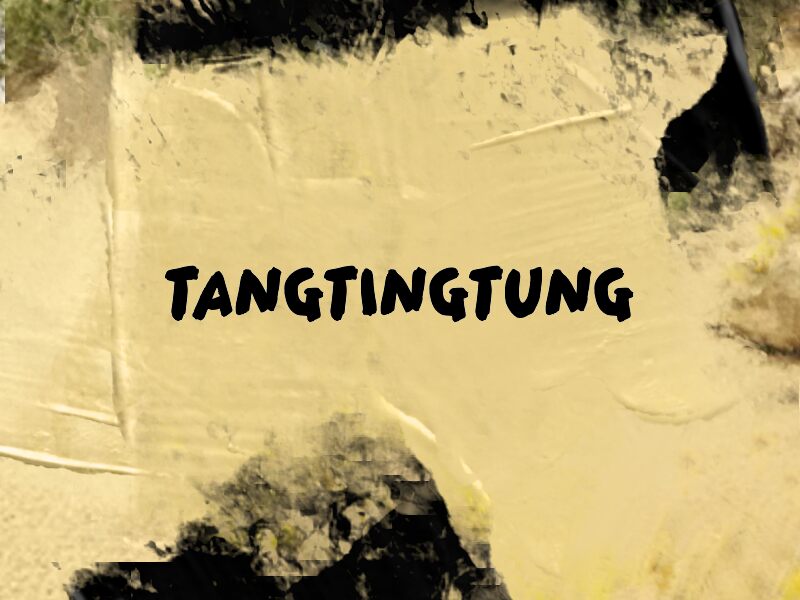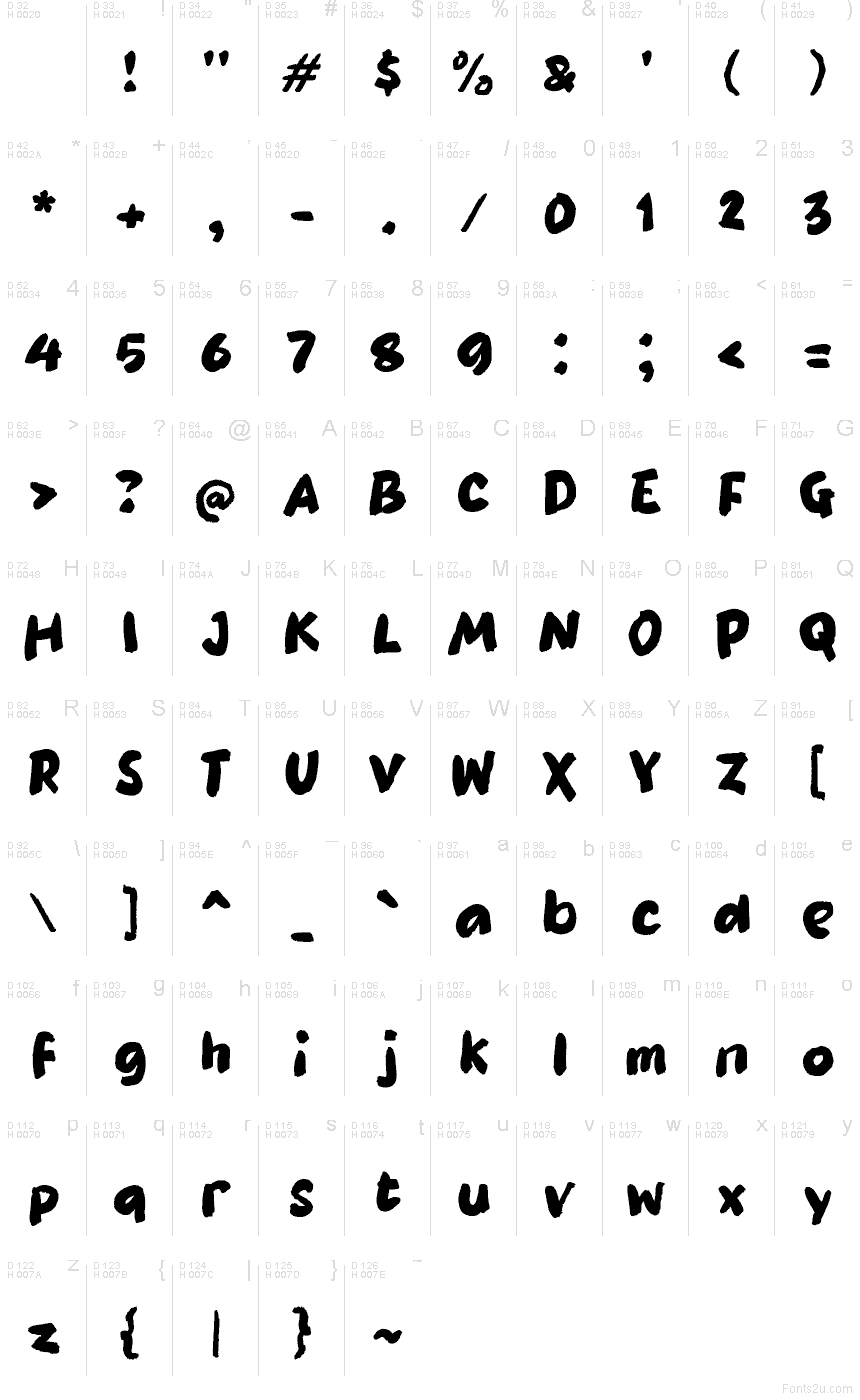
TANGTINGTUNG
Tangtingtung di Wep è un font brush gratuito con un carattere ruvido e dipinto a mano. Le lettere appaiono larghe e schiette, con tratti corposi, bordi irregolari e un leggero movimento irregolare che conferisce all'intero font un'estetica da poster urbano, piuttosto che la finitura pulita di un lettering professionale.
È ideale per flyer musicali, grafiche per skateboard, copertine di fanzine, packaging audaci e titoli che richiedono una carica rapida e artigianale. Come font gratuito, Tangtingtung funziona bene anche per titoli di copertina, slogan per merchandising e headline d'impatto, poiché le maiuscole trasmettono una densa energia da pennellata che sembra più un grido dipinto che una calligrafia curata.